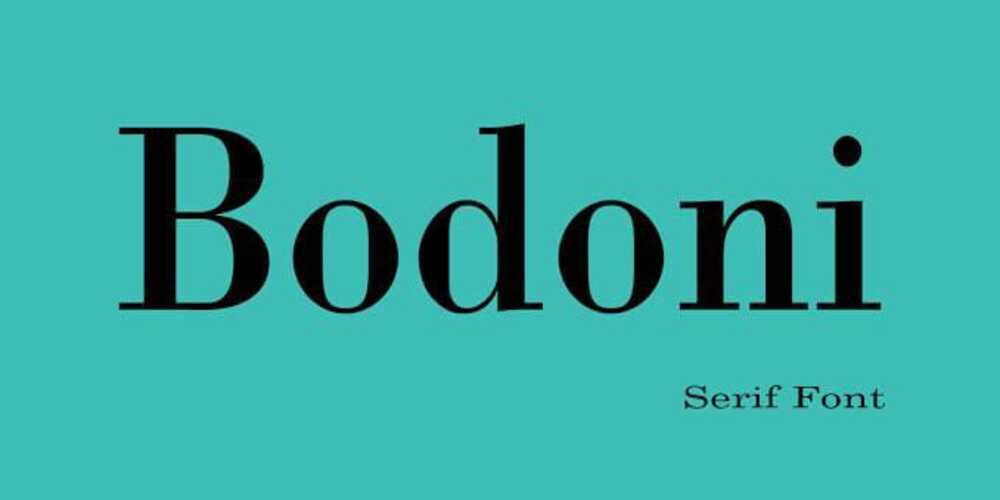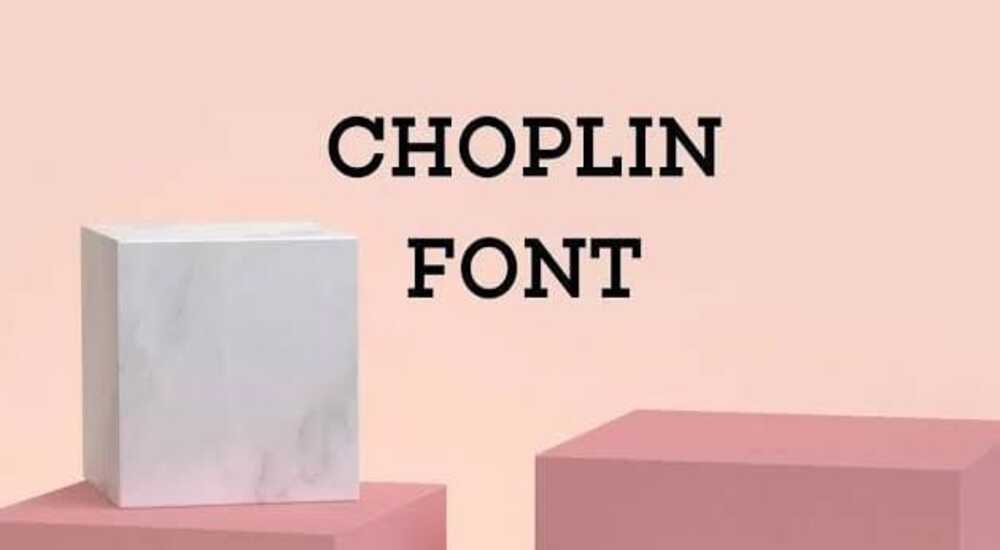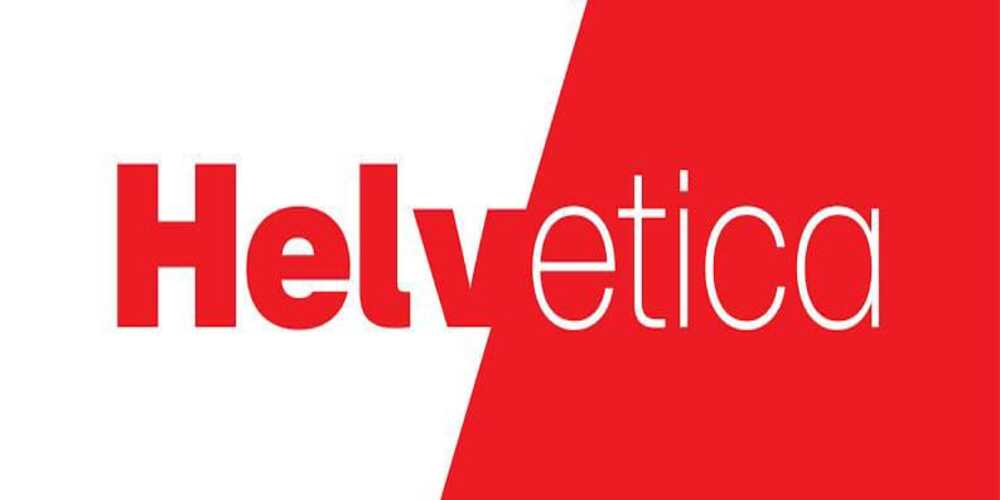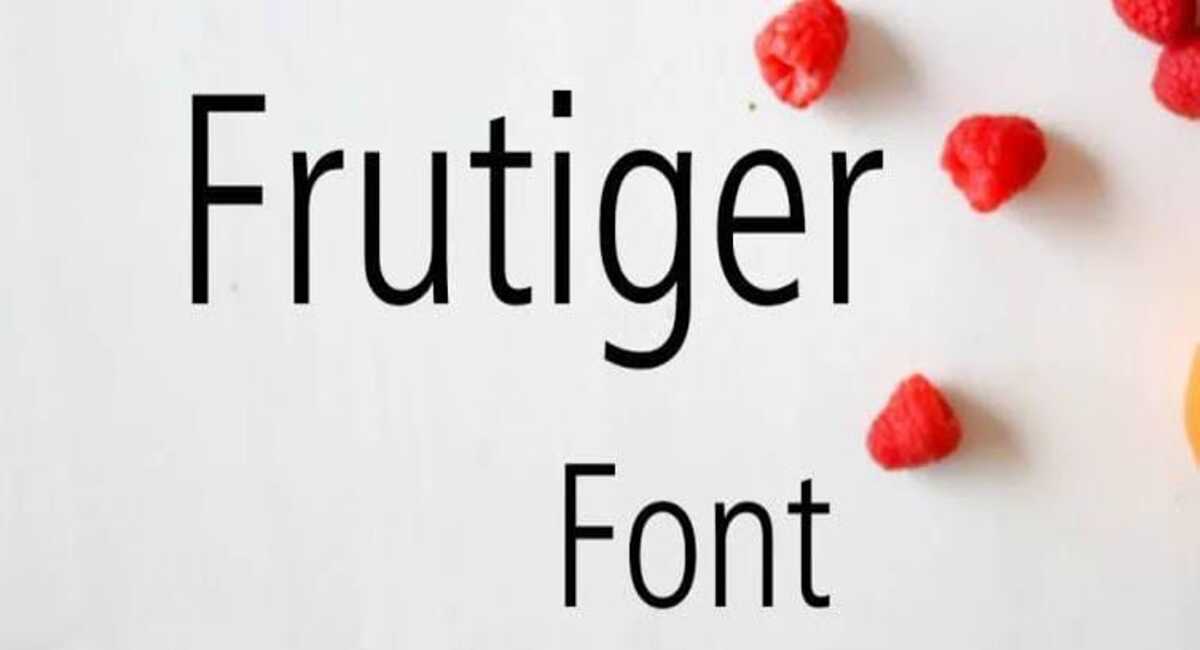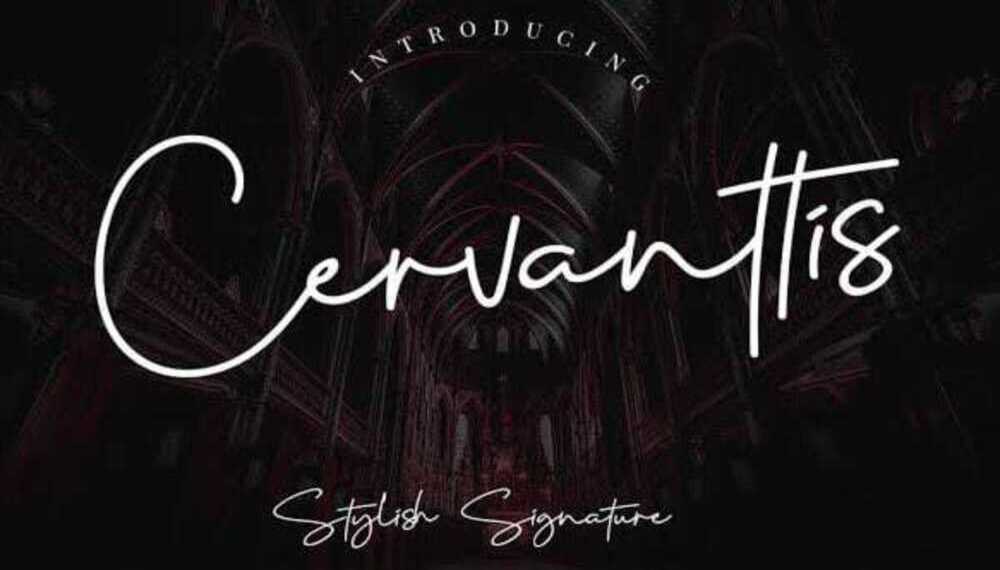
10 Rekomendasi Font Keren untuk Logo Terbaik 2024
Rekomendasi Font Keren untuk Logo – Tahukah kamu jika jenis font unik itu ada banyak sekali macamnya. Nah, pemilihan font untuk logo menjadi hal yang sangat penting untuk diperhatikan.
Sebab, logo merupakan identitas yang paling mudah dikenali dari sebuah brand, perusahaan, maupun lembaga apapun bidangnya. Untuk itu, pembuatan logo tidak boleh sembarangan.
Biasanya logo mengandung beberapa unsur penting, mulai dari nama brand, warna yang jadi ciri khas, tagline hingga font unik dan ikonik.
Salah satu yang harus diperhatikan adalah font yang digunakan, agar bisa tampil berbeda dan memiliki ciri khas tersendiri. Nah, untuk itu kamu perlu memilih huruf yang keren ketika membuat logo. Berikut ini rekomendasi huruf keren dan unik yang bisa kamu jadikan pilihan.
Rekomendasi Font Keren untuk Logo
1. Bodoni
Rekomendasi font untuk logo yang pertama ini adalah buatan Giambattista Bodoni. Huruf unik satu ini memiliki kontras antara garis tipis dan tebal yang terbilang tak biasa.
Bisa dikatakan jika jenis font unik satu ini cukup populer dan ikonik, karena digunakan dalam logo brand Vogue hingga Calvin Klein. Huruf Bodoni ini sangat cocok untuk digunakan membuat logo brand fashion karena memberikan kesan mewah dan eksklusif.
2. Garamond
Jenis font unik selanjutnya ini merupakan rancangan dari Claude Garamond bersama Jean Jannon yang sudah ada sejak abad ke-16. Ini merupakan huruf turunan dari huruf Serif, jangan heran jika terlihat cukup ekspresif.
Huruf Garamond ini digunakan untuk pembuatan logo American Eagle yang keren dengan mengusung konsep minimalis. Jenis huruf semacam ini dijamin bakal memberikan kesan keren yang timeless.
3. Huruf Choplin
Jenis font unik berikutnya yang cocok sekali untuk membuat logo adalah huruf yang dinamakan Choplin. Ini merupakan hasil karya seorang desainer berkebangsaan Jerman, bernama Rene Bieder. Tampilan yang terlihat dari huruf ini punya kesan yang kuat, modern, dan minimalis.
Jenis font keren untuk logo ini kerap digunakan untuk membuat layout fotografi maupun menunjukkan branding secara jelas dan juga tegas. Tak jarang, huruf ini juga kerap digunakan untuk pembuatan logo sebuah majalah.
4. Southwave
Rekomen font keren untuk logo berikutnya ini memiliki karakteristik seperti kaligrafi modern. Memiliki fitur One Type, jenis font unik ini sangat cocok jika digunakan untuk keperluan desain, termasuk di acara pernikahan, logo, stiker, t-shirt, dan banyak karya menarik lainnya.
Jenis huruf yang satu ini juga support berbagai macam karakter, dan simbol, termasuk mendukung multi bahasa. Secara umum, Southwave digunakan untuk pembuatan logo brand-brand makanan.
5. Helvetica
Jenis font unik yang satu ini sudah tak asing lagi di dunia desain grafis. Hingga saat ini Helvetica masih jadi salah satu font keren yang banyak digunakan dalam pembuatan logo.
Huruf yang sudah ada sejak tahun 1984 ini mampu memberikan kesan simpel, namun tetap profesional pada logo yang dibuat. Meskipun demikian, banyak yang kurang menyukainya, sebab jarak antara satu huruf dengan huruf lainnya terlalu sempit.
Sehingga, penting untuk memperhatikan secara detail apakah benar-benar cocok untuk logo yang ingin dibuat.
6. Reckoner
Rekomendasi font untuk logo selanjutnya ini merupakan buatan Alex Dale dan terinspirasi dari huruf Sans Serif populer, misalnya Neue, Alegre & Dharma Gothic.
Huruf Reckoner ini didesain dengan memberikan sentuhan modern tapi tetap mempertahankan huruf basic secara tradisional.
Menariknya lagi, Reckoner merupakan salah satu font keren dan gratis yang bisa kamu pakai secara personal maupun komersial. Salah satunya untuk membuat desain logo brand yang sesuai karakter.
7. Frutiger
Lanjut ada Frutiger sebagai salah satu font keren untuk logo yang bisa jadi pilihan menarik. Jenis huruf yang didesain oleh Adrian Frutiger ini masuk dalam kategori huruf Sans Serif.
Bentuk huruf unik ini telah lama ada dan populer sejak 1975 dan mulai digunakan di banyak tempat. Salah satunya di Bandara Internasional Charles De Gaulle, bandara yang baru saja dibangun di kota Roissy, Perancis.
Bentuk huruf ini memiliki karakteristik huruf-huruf yang terlihat tegas dan jelas serta tidak terlalu berdekatan. Frutiger bahkan sudah digunakan untuk huruf tertulis di buku paspor Swiss sampai saat ini. Jangan heran jika Frutiger bisa jadi opsi terbaik font untuk logo yang keren.
8. Minimalust
Tahukah kamu, ada font keren buatan anak negeri yang diakui dan banyak digunakan dalam dunia desain grafis, lho. Huruf buatan Pratama Yudha ini diberi nama Minimalust dan jadi salah satu huruf populer dalam seni desain grafis.
Jenis font unik ini masuk dalam jajaran Sans Serif vintage dengan karakteristik minimalis yang memiliki tepian halus. Desainnya sendiri terinspirasi dari bentuk tulisan tangan dan juga pencetakan vintage.
Font keren untuk logo ini mampu memberikan kesan elegan namun tidak berlebihan. Blenda Script cocok sekali digunakan untuk membuat background yang polos supaya tampak minimalis.